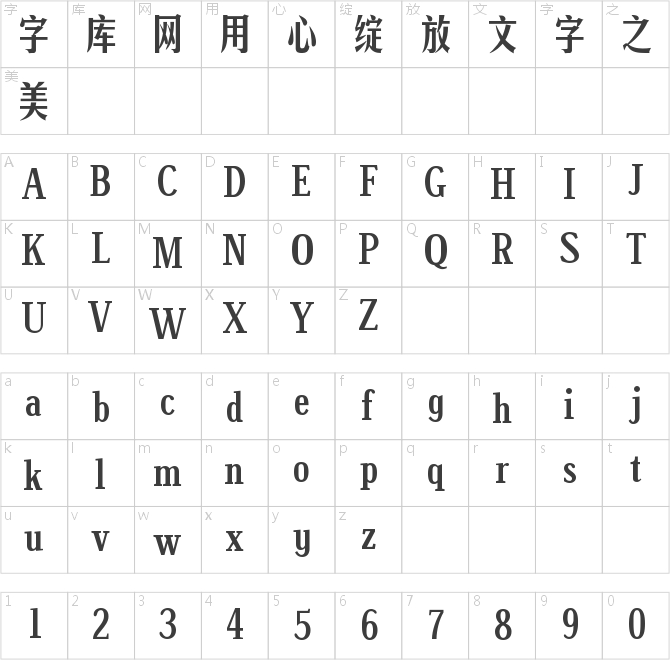
字體管家字體打包 詳情頁
字體名稱: 字體管家字體打
字體類型: 字體打包
字體管家字體打包
字體管家字體下載共有23個字體,演示字體為:字體管家版宋
字體管家字體打包字體字庫是一款讓人賞心悅目、百看不厭的字體打包,適合各類廣告和產品包裝設計應用,字體大小2.68MB,格式為ttf字體,上傳用戶是Aa字庫,作者/版權方為字體管家